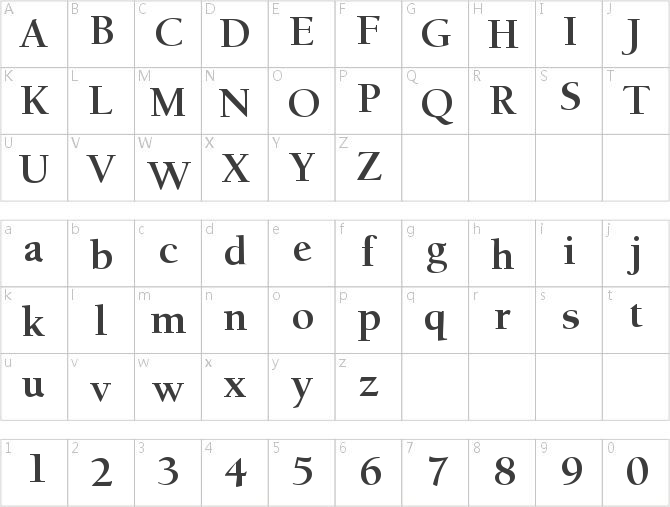
字體名稱(chēng): Bergman
BergmannOldStyle
BergmannOldStyle介紹
BergmannOldStyle字體字庫(kù)是一款讓人賞心悅目、百看不厭的英文字體,適合各類(lèi)廣告和產(chǎn)品包裝設(shè)計(jì)應(yīng)用,字體大小0.05MB,格式為ttf字體,上傳用戶是手機(jī)洗相,作者/版權(quán)方為未知